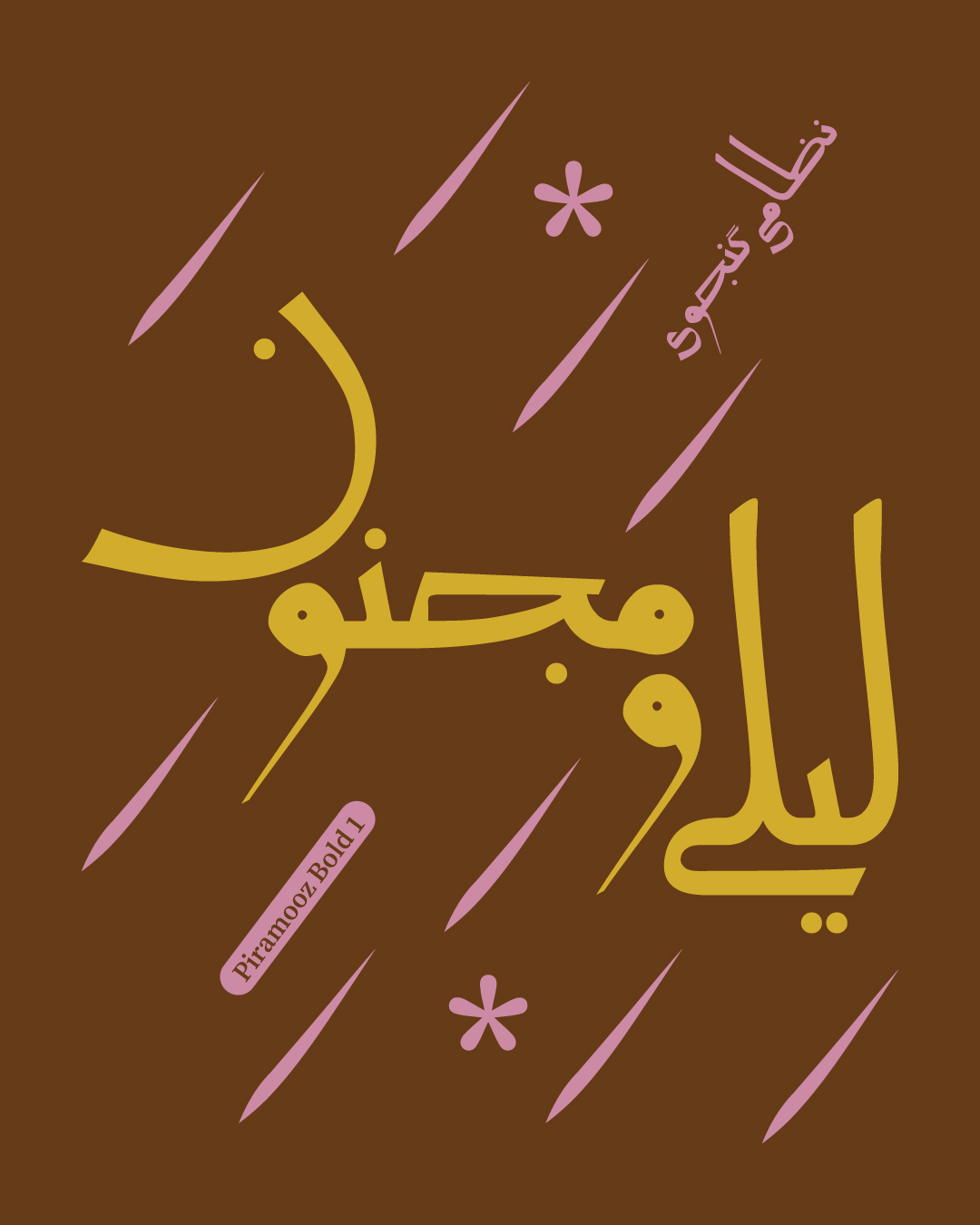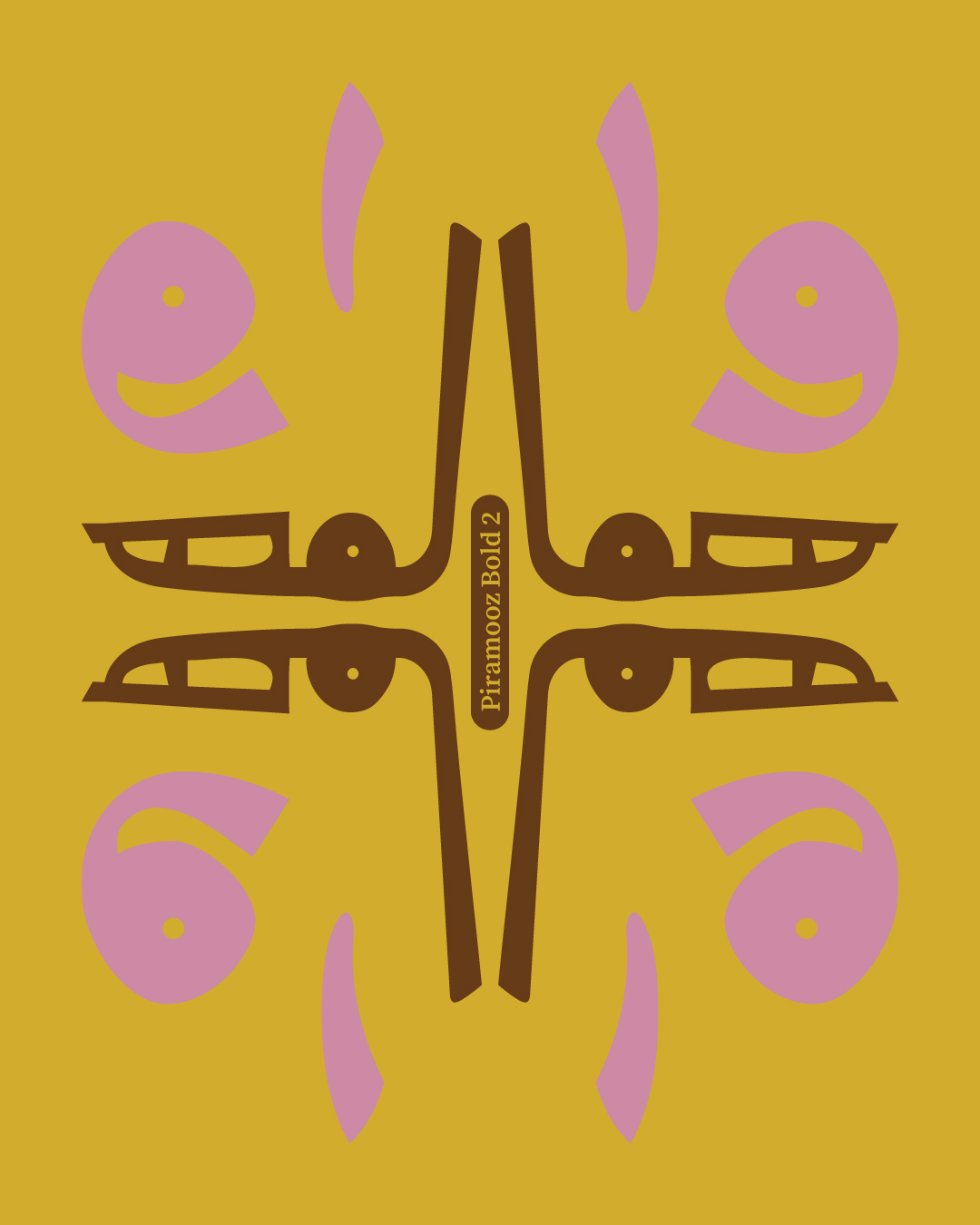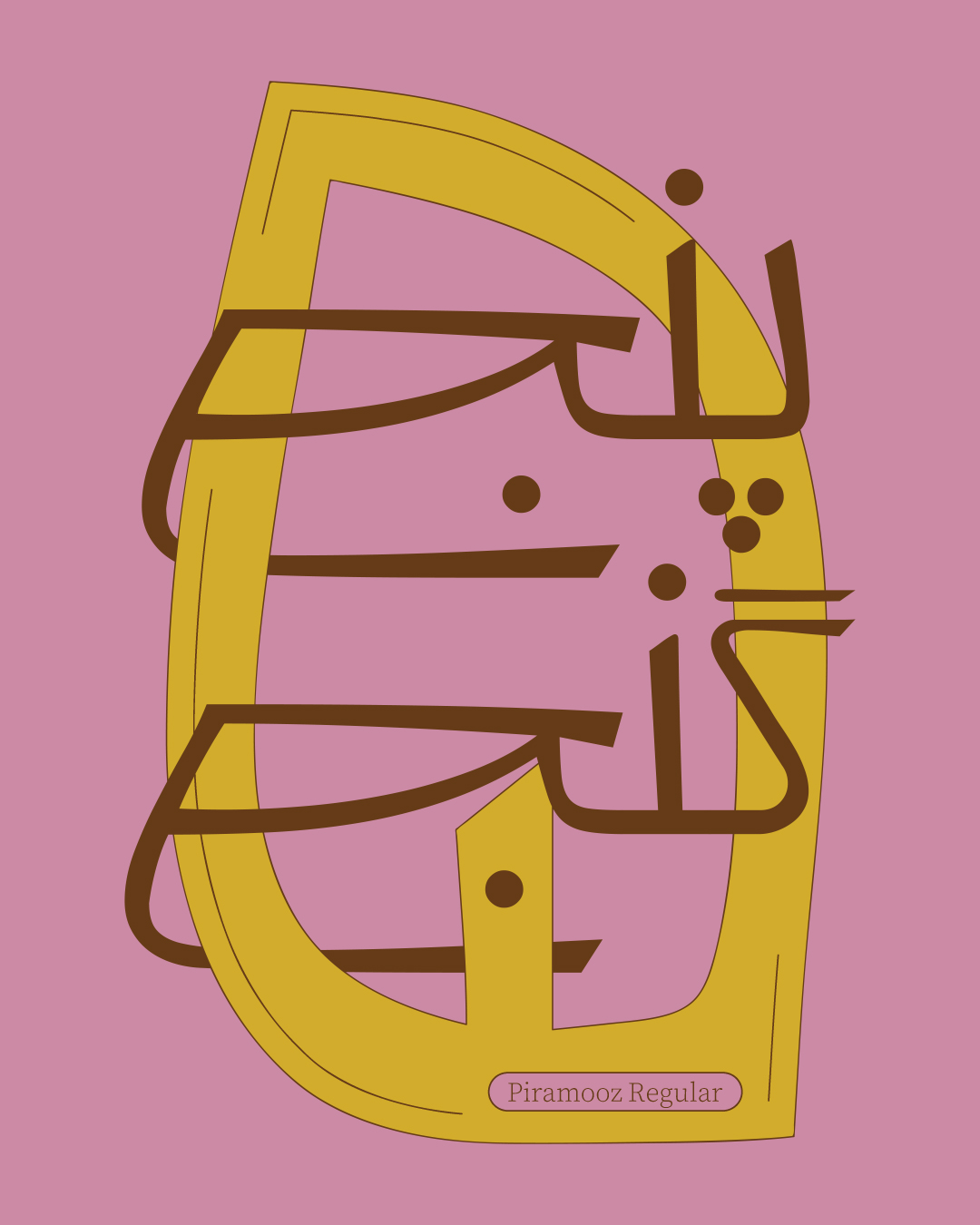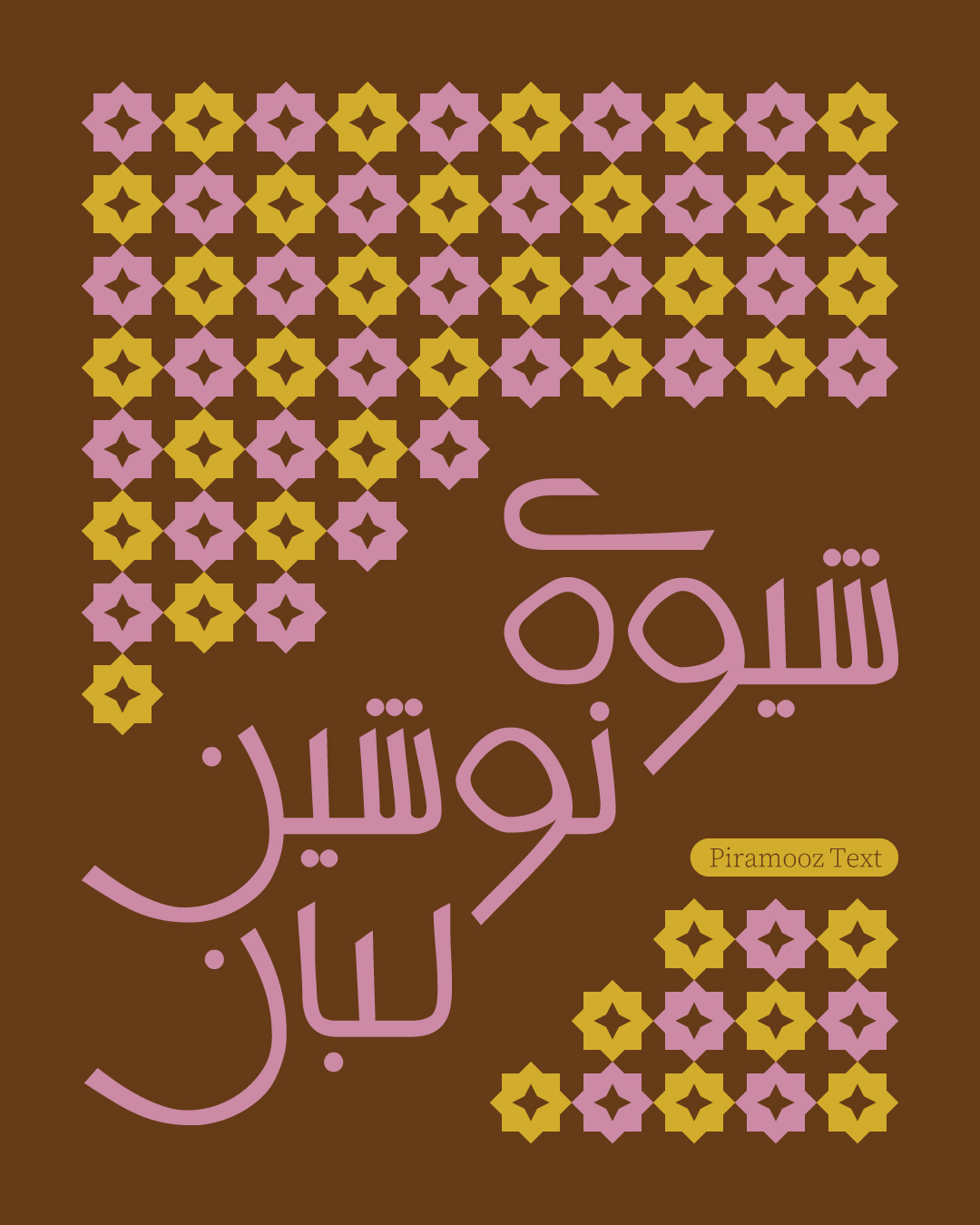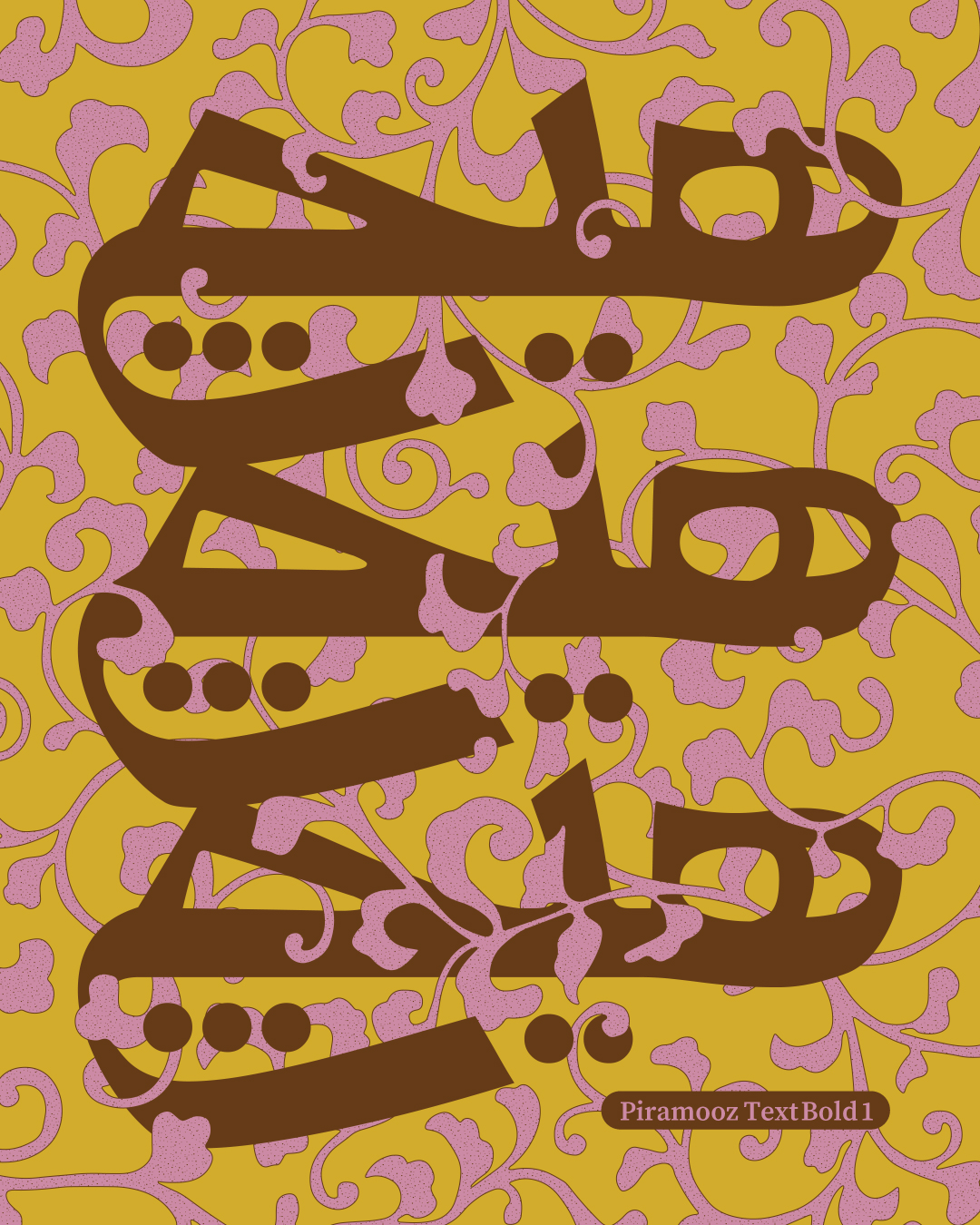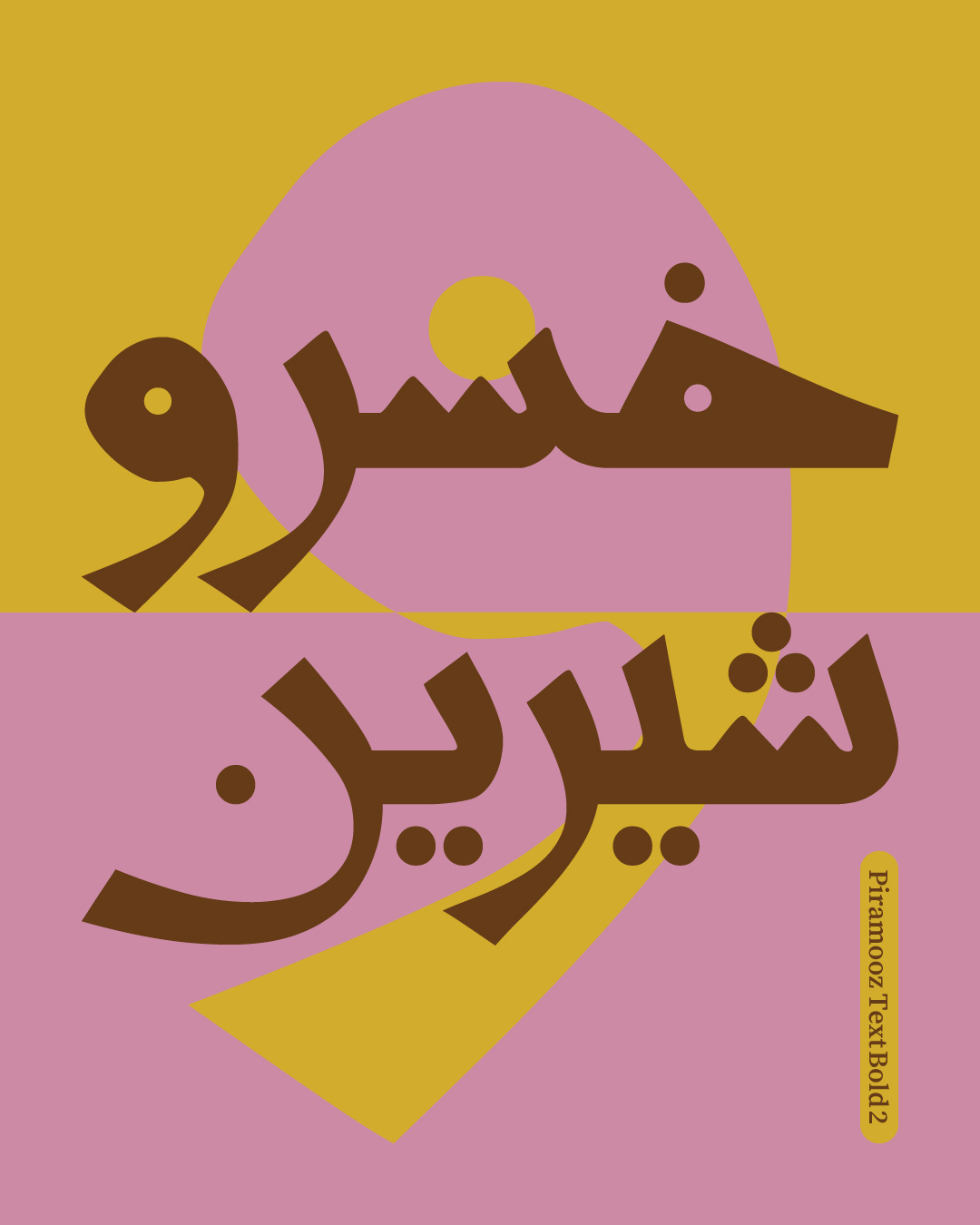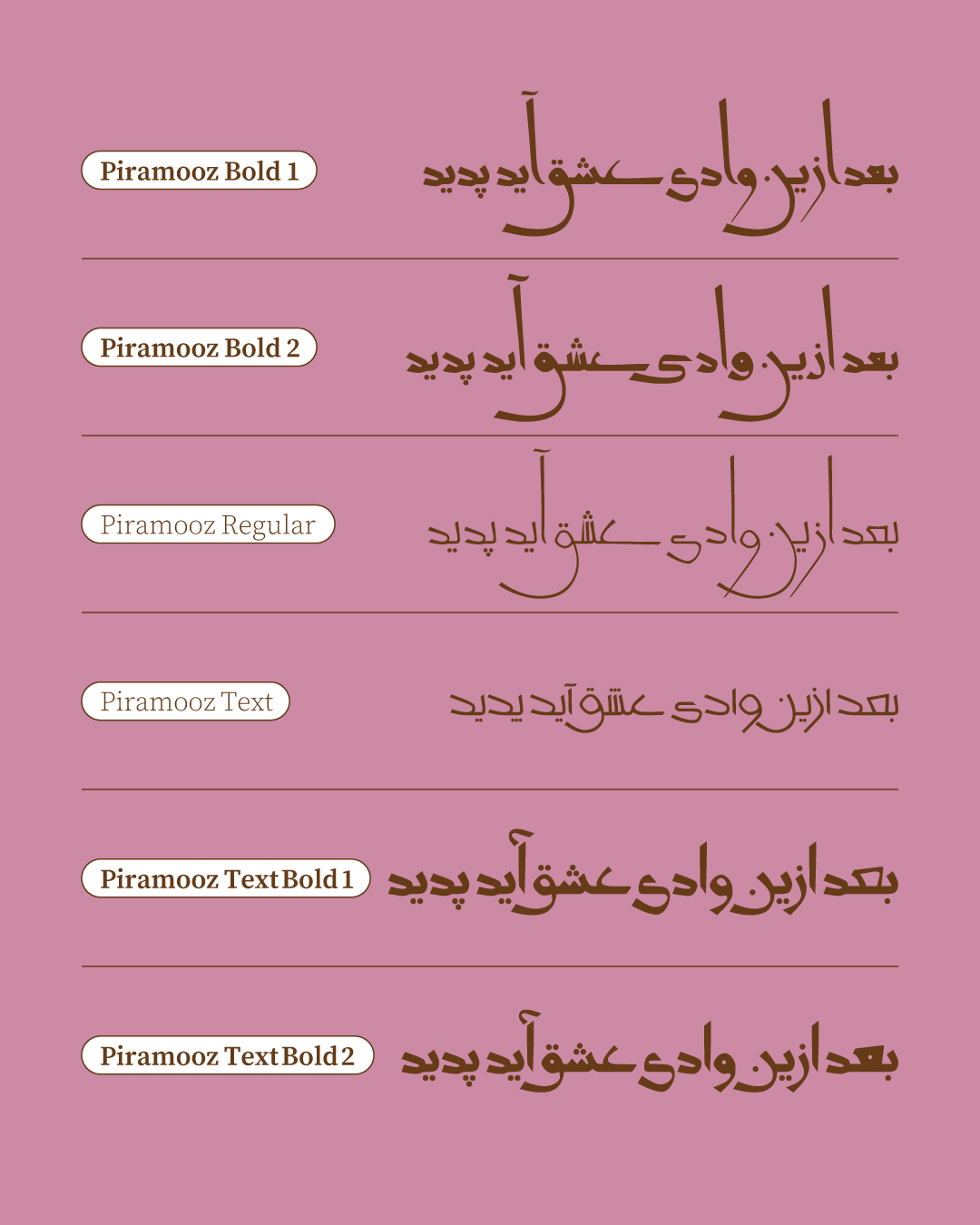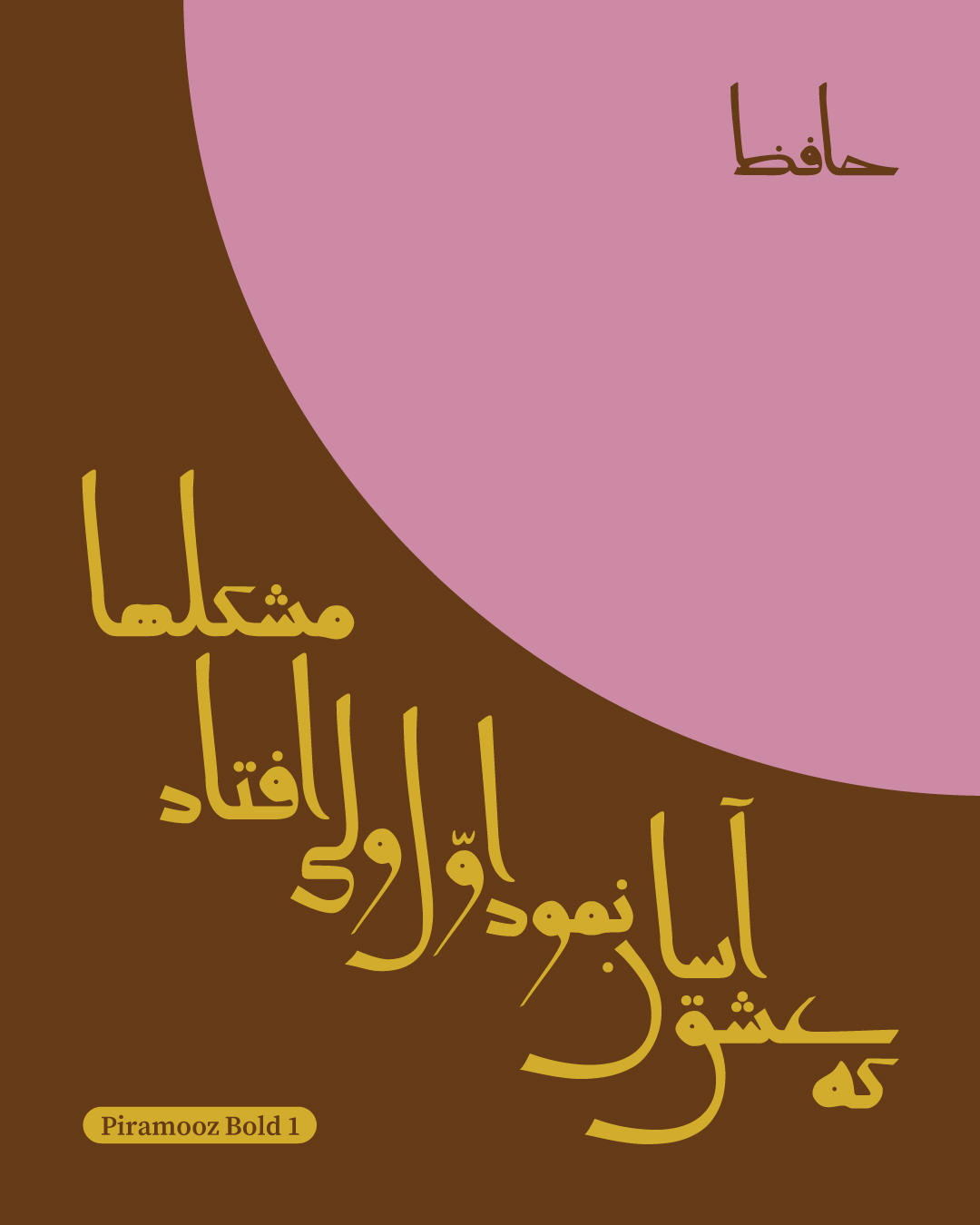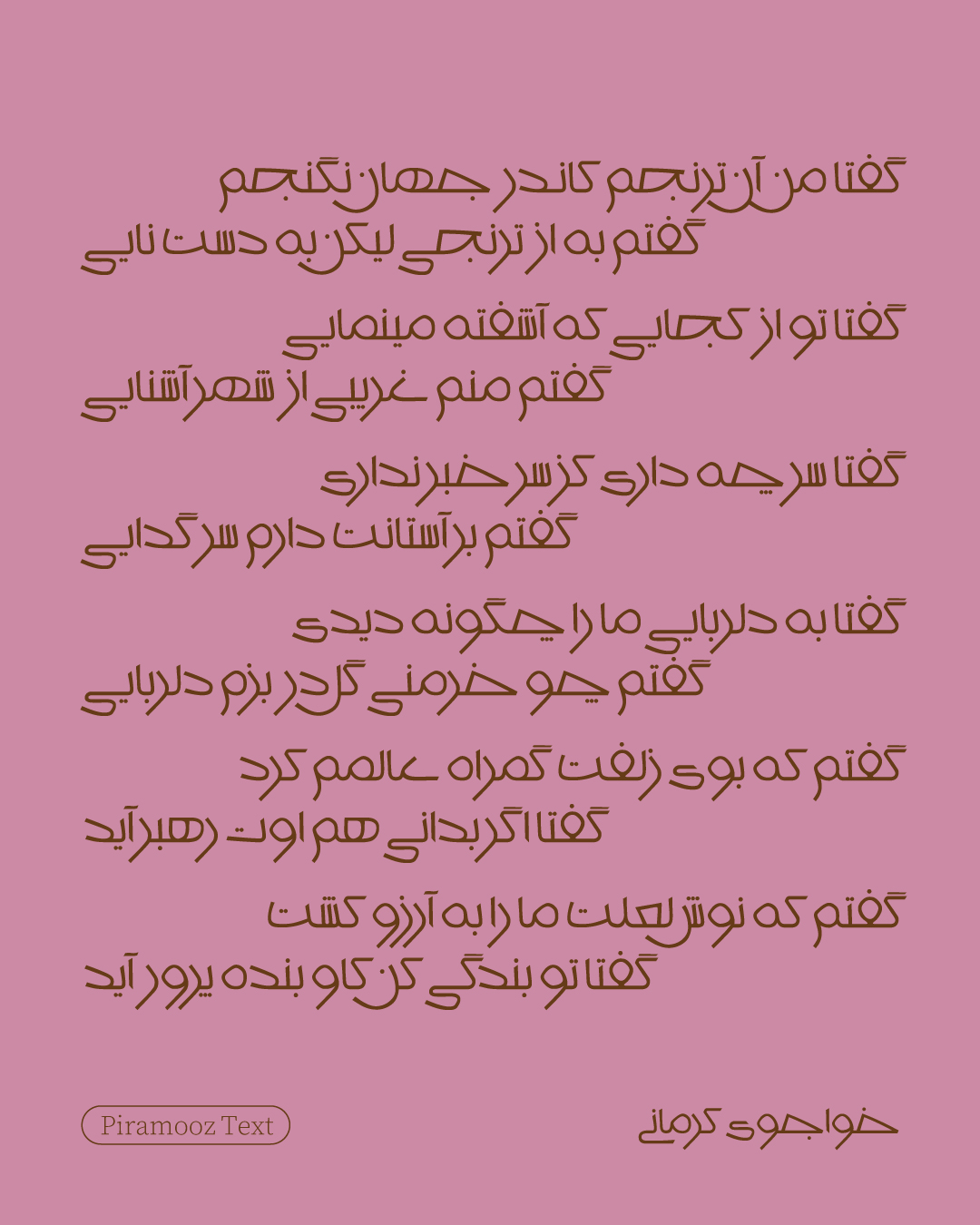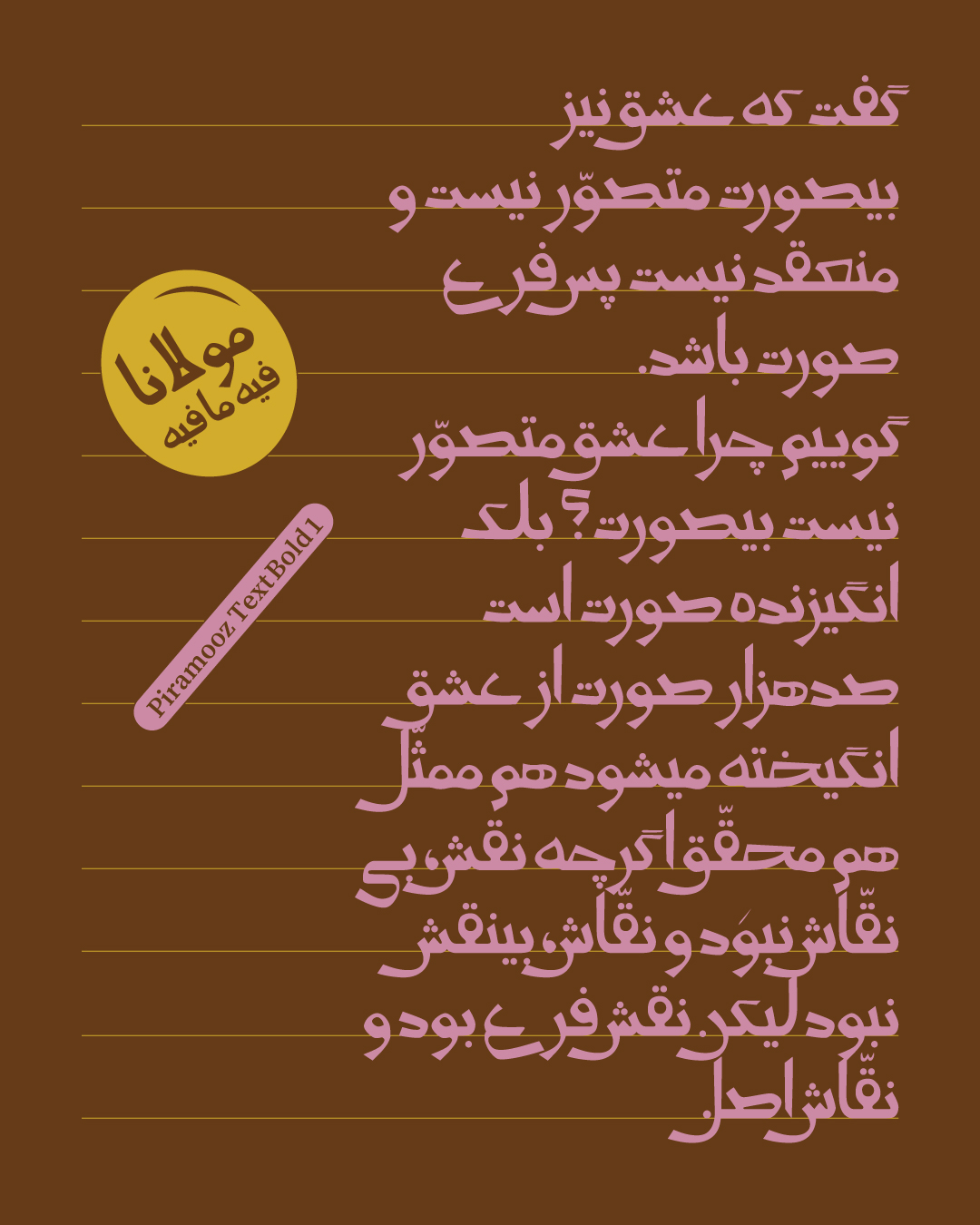
قلم پیرآموز font Piramooz
قلم پیرآموز
کاری از هما دلورای
درباره قلم پیرآموز
طراحان و توسعه دهندگان
طراح قلم
هما دلورای
طراح گرافیک و هنرمند
هما دلورای، هنرمند ایرانی ساکن تهران، پس از فارغ‌التحصیلی در رشتهٔ ارتباط تصویری از دانشگاه تهران در سال ۱۳۸۵، فعالیت حرفه‌ای خود را با تمرکز بر پروژه‌های فرهنگی و هنری آغاز کرد.
حوزه‌های فعالیت
• طراحی پوستر، کتاب، هویت بصری و تایپوگرافی
• همکاری با مؤسسات فرهنگی و هنری در ایران، اروپا و آمریکا
• طراحی نخستین فونت خود، «پیرآموز»، زیر نظر رضا عابدینی در سال ۱۳۸۶
• برگزاری کارگاه‌های تایپوگرافی و پوستر در ایران، بلژیک و لبنان
• داوری چندین مسابقهٔ بین‌المللی طراحی پوستر
آثار او در بیش از ۱۰۰ نمایشگاه و فستیوال داخلی و بین‌المللی به نمایش درآمده و جوایز متعددی در طراحی گرافیک کسب کرده است.
در سال‌های اخیر، فعالیت هنری او به طراحی کتاب هنرمندانه، مجسمه‌سازی و چیدمان گسترش یافته است. آثارش در مجموعه‌هایی از جمله موزهٔ آرمیتاژ روسیه، موزهٔ اسمیتسونیان نیویورک و موزهٔ هنرهای تزئینی پاریس نگهداری می‌شود.